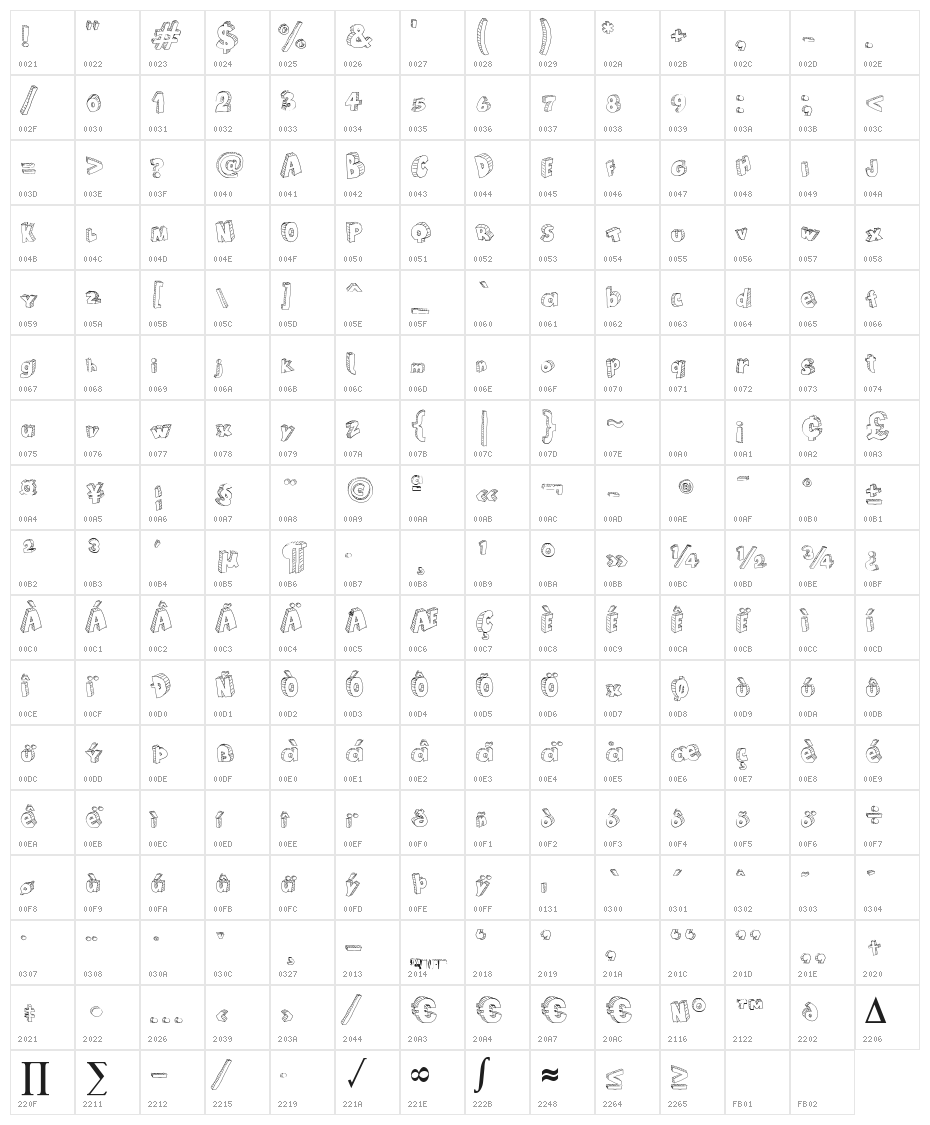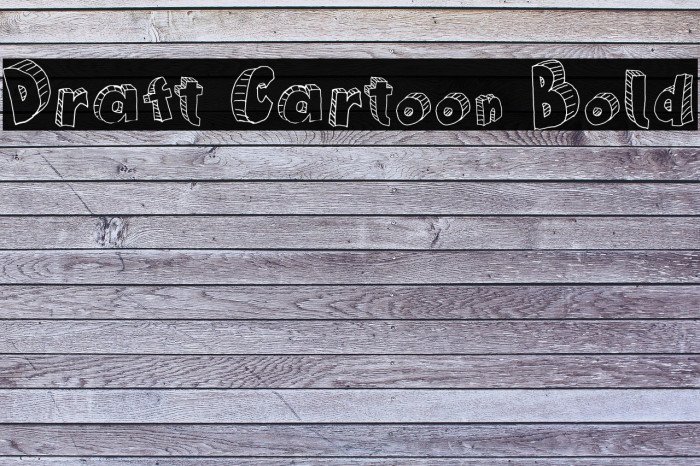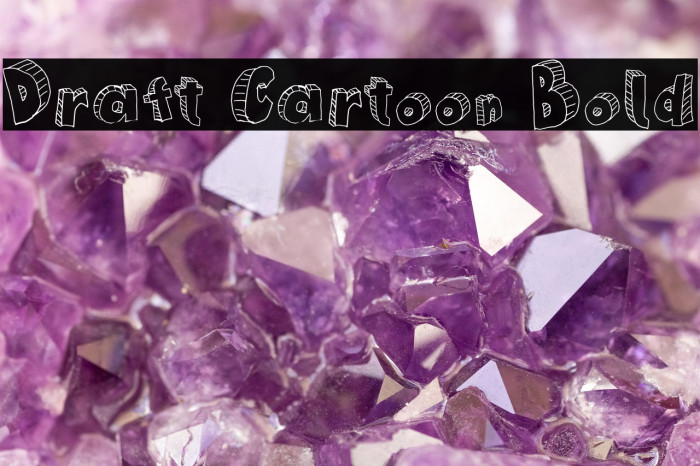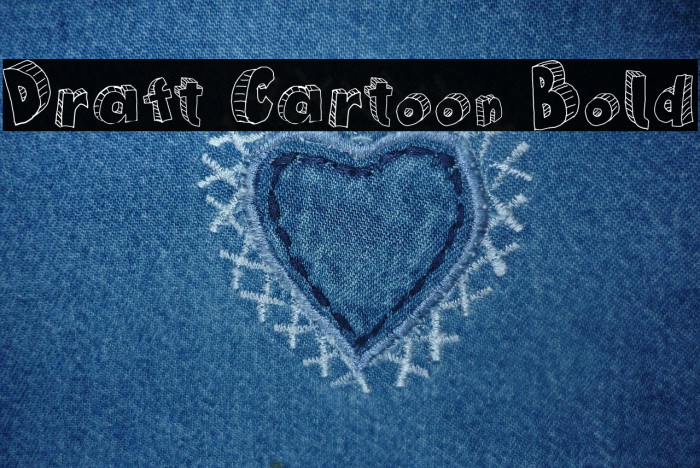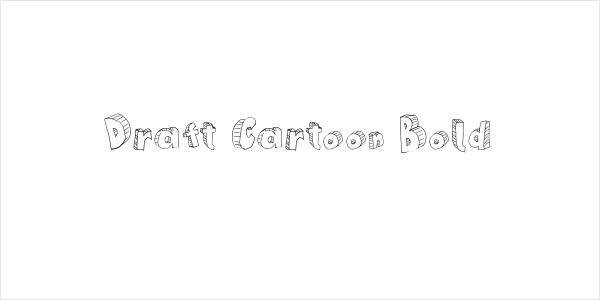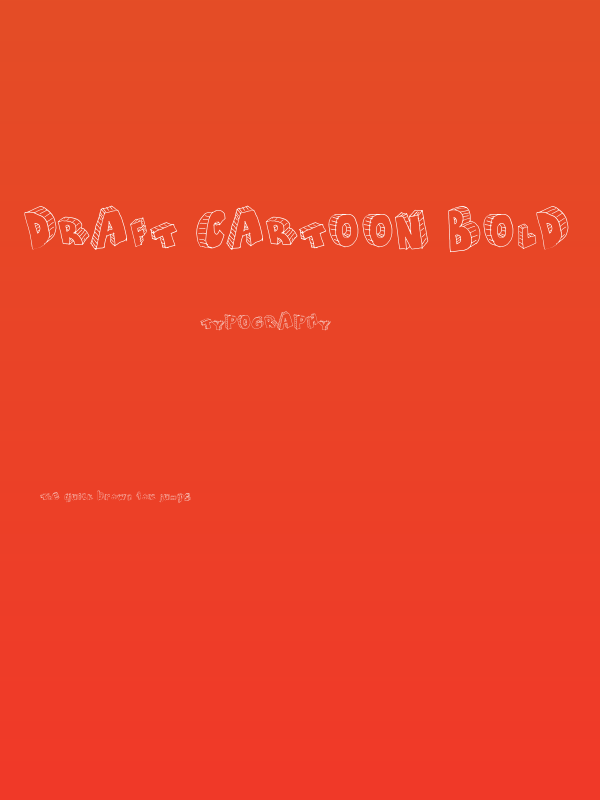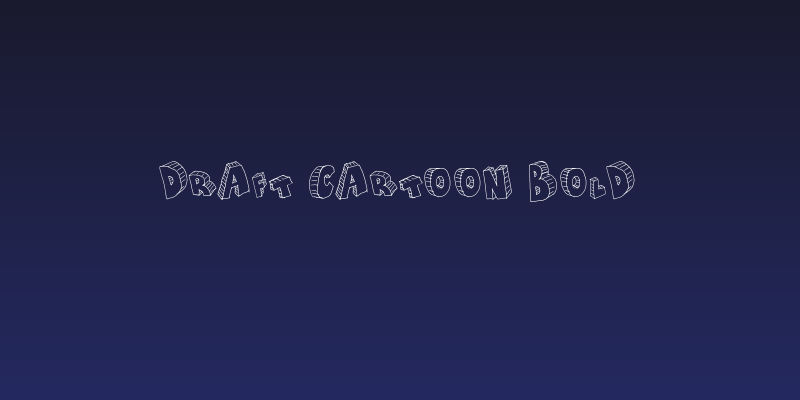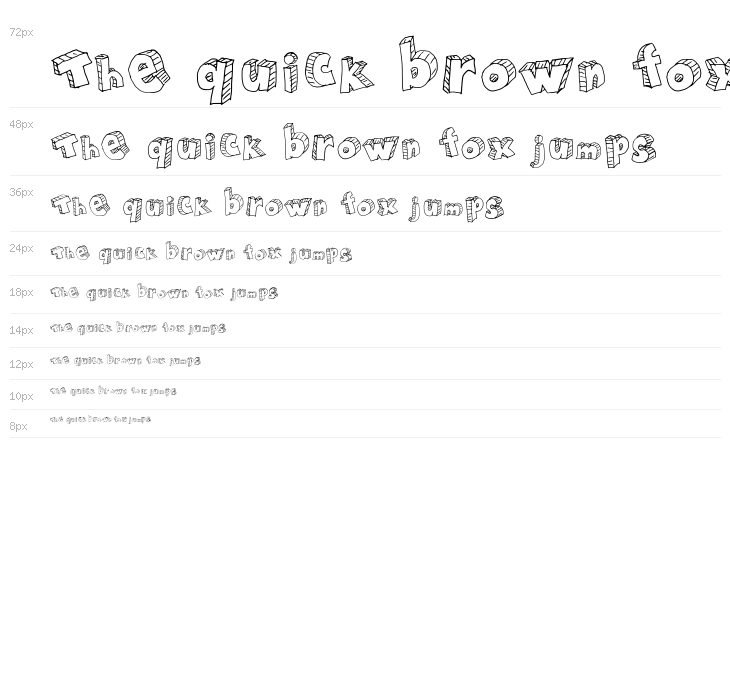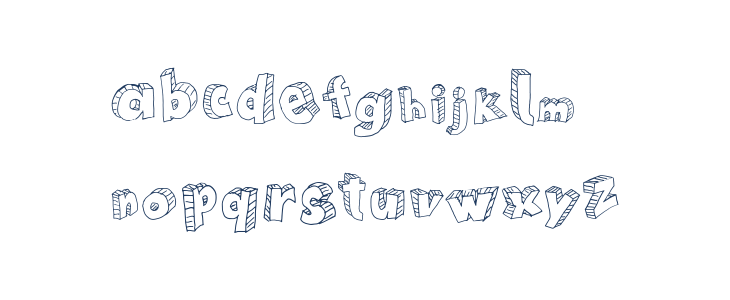
Draft Cartoon Bold Font
| Style général | Playful, Cartoonish, Hand-drawn |
| Cas d'utilisation | Headlines, Posters, Branding |
| Projets proposés | Ideal for children's books, comic strips, playful branding, posters, and greeting cards. |